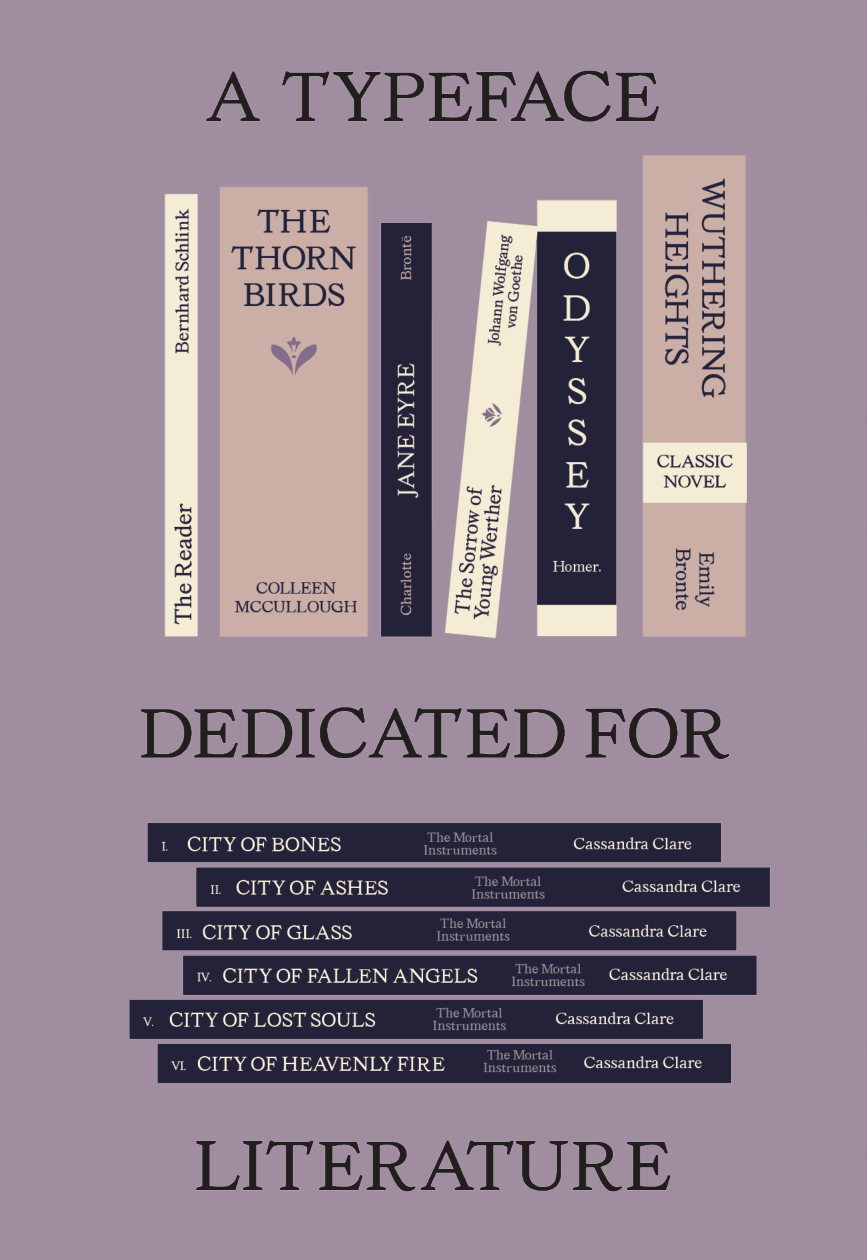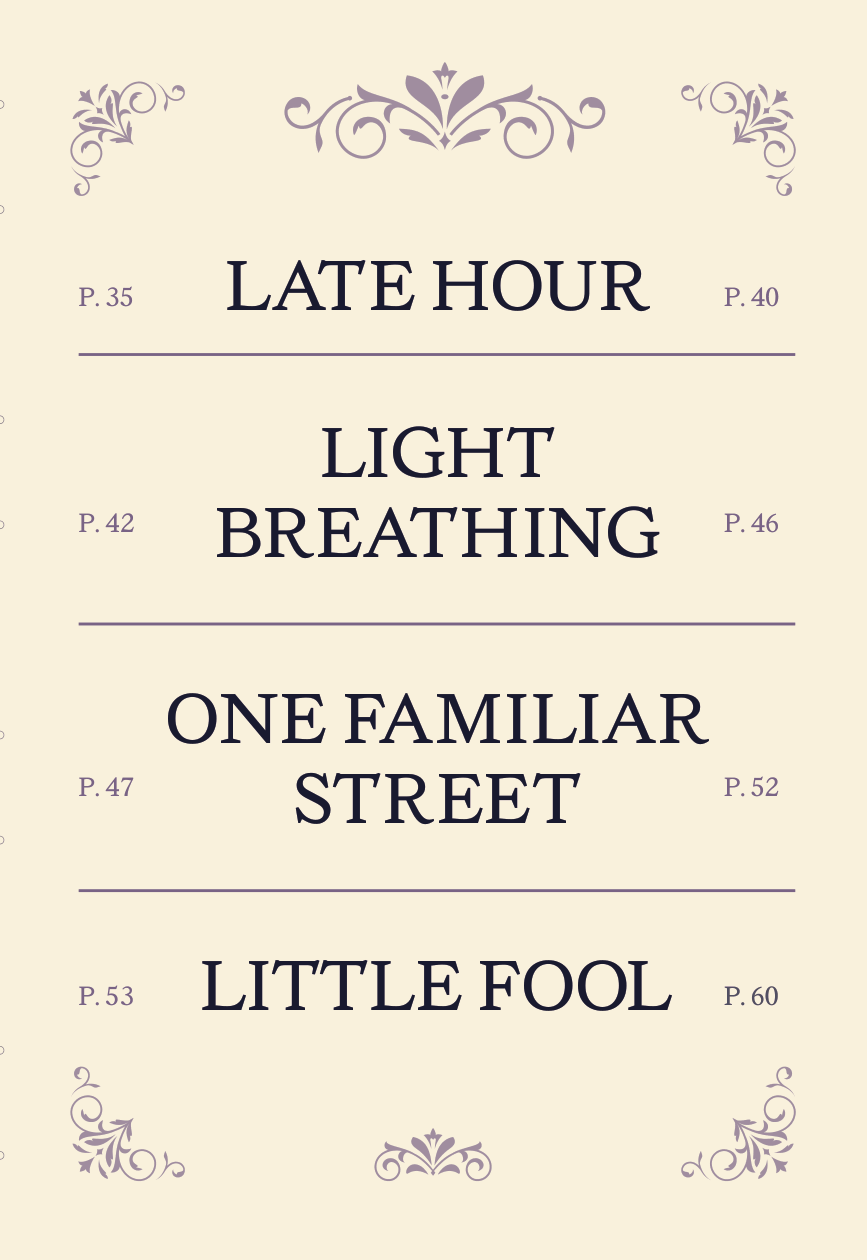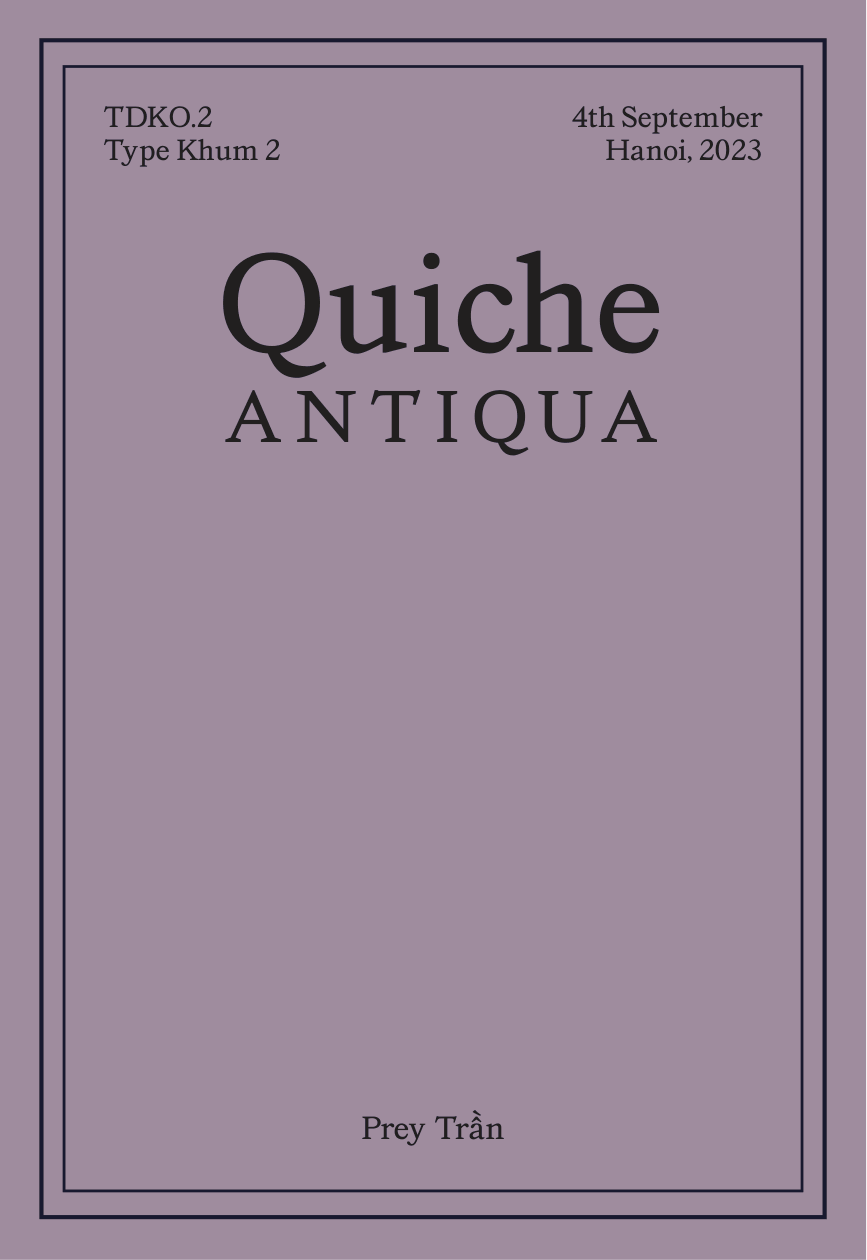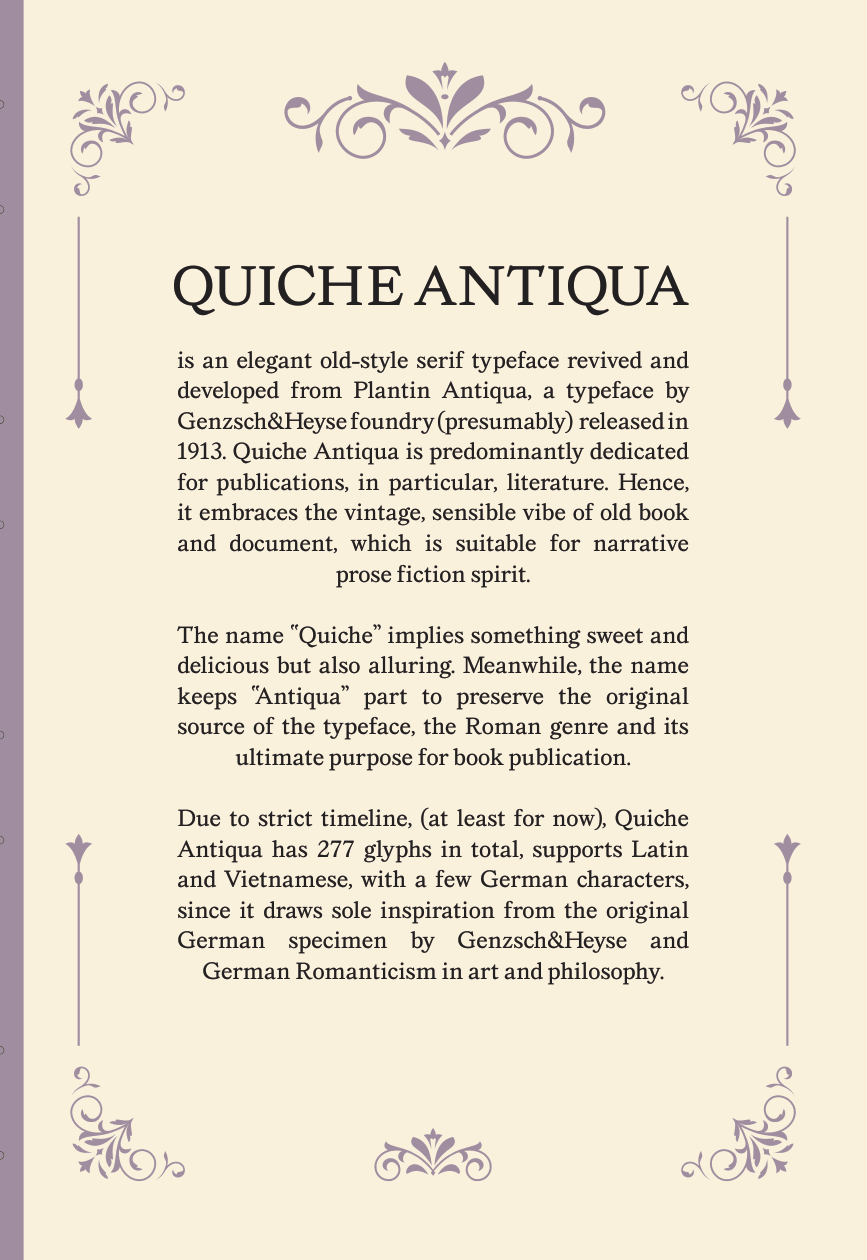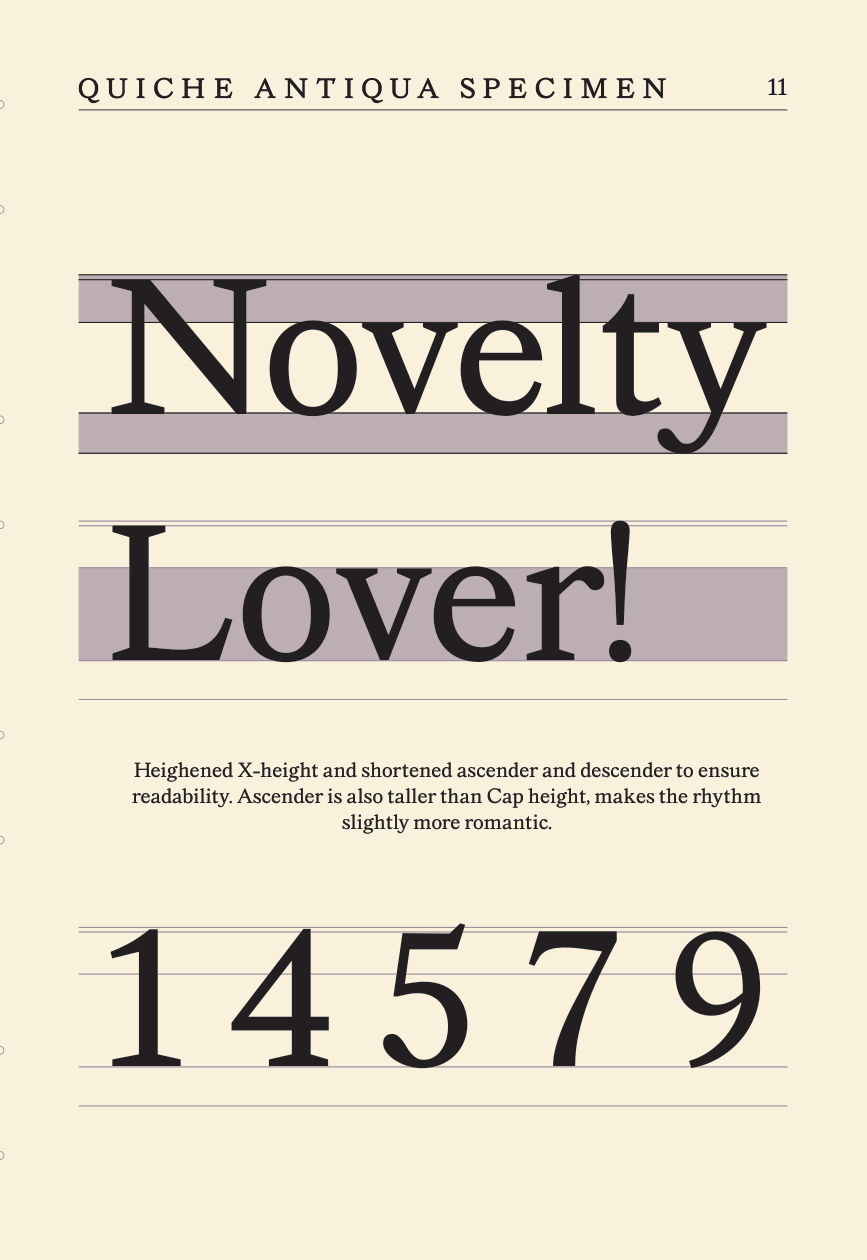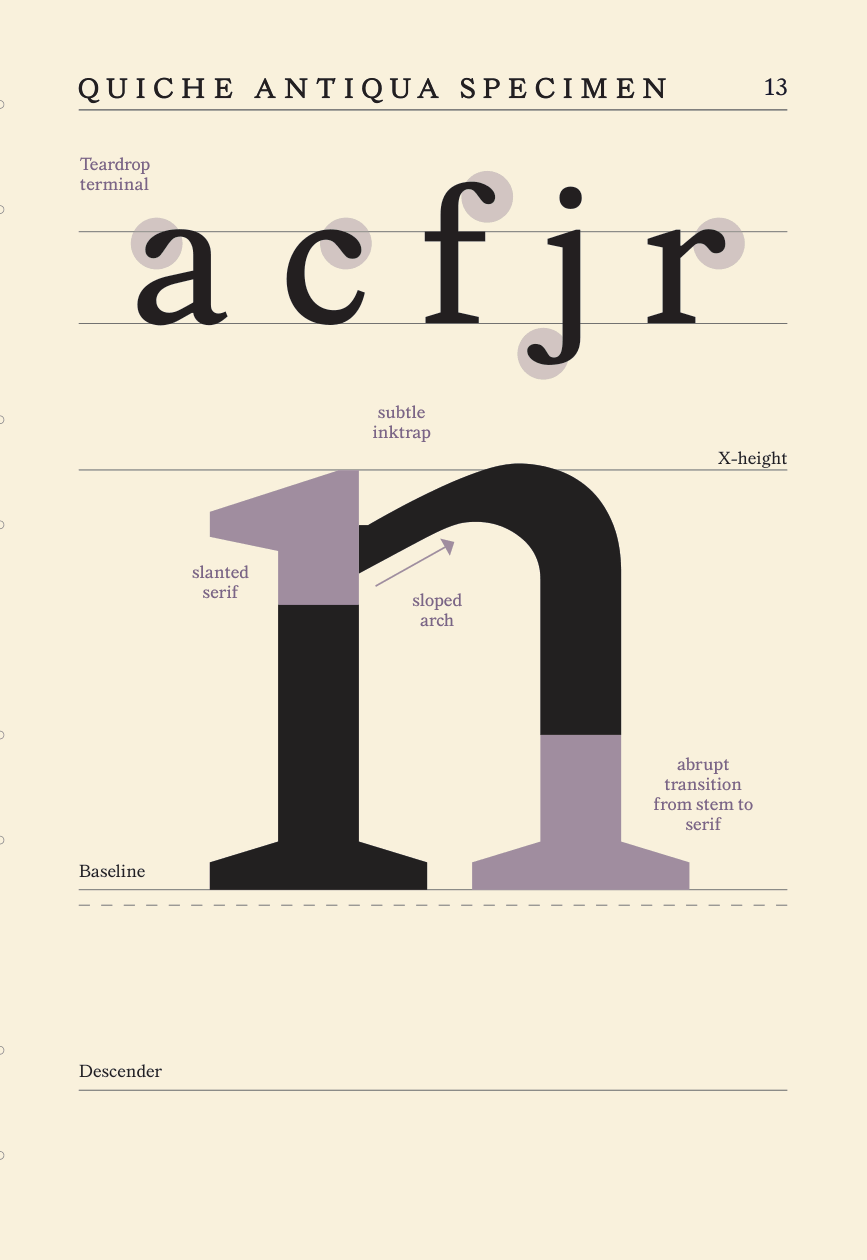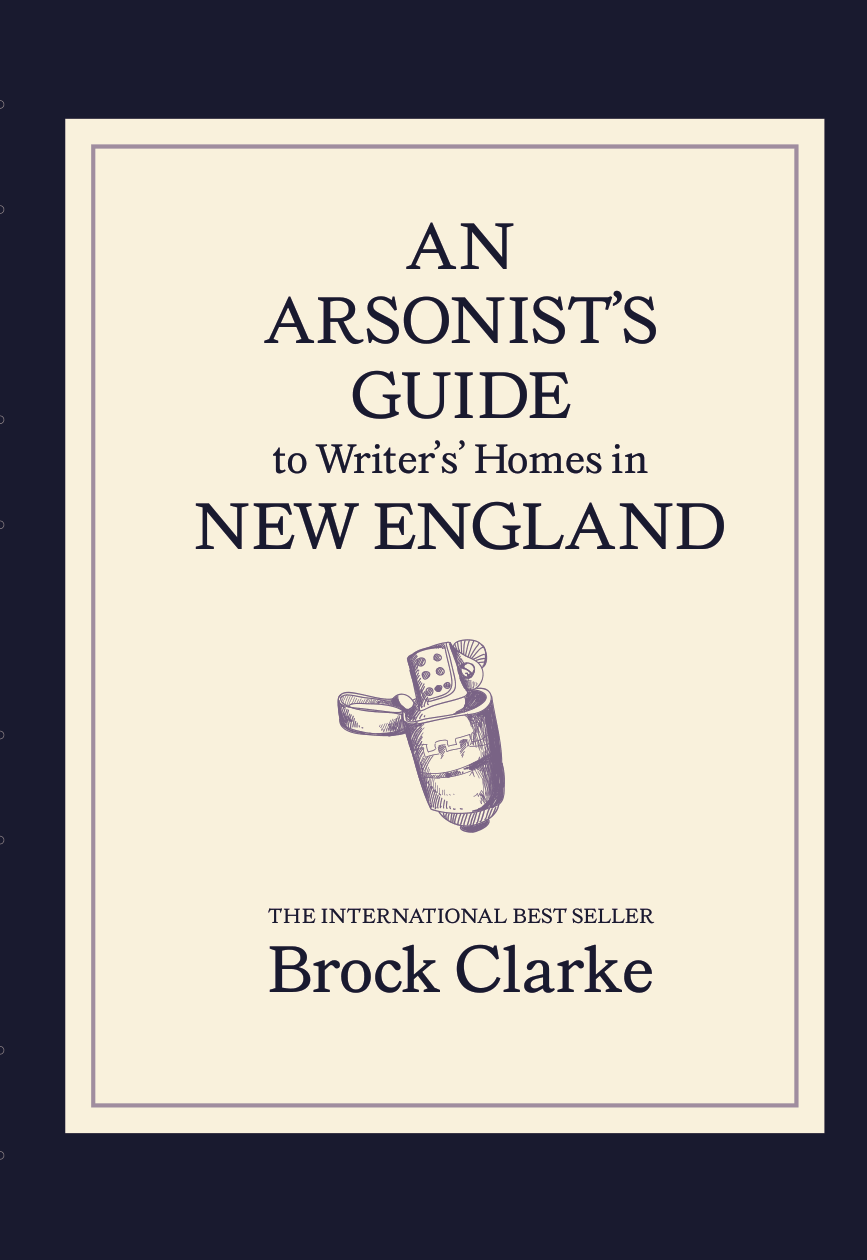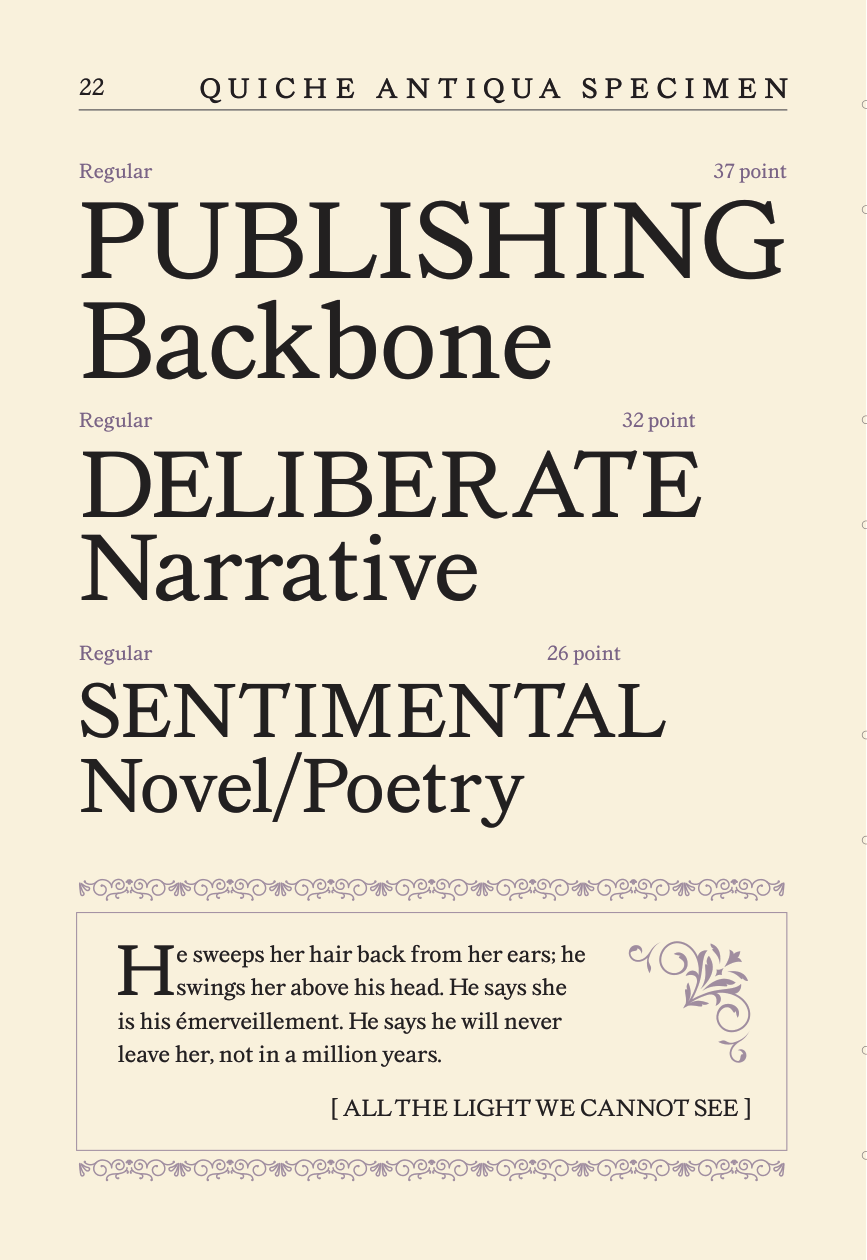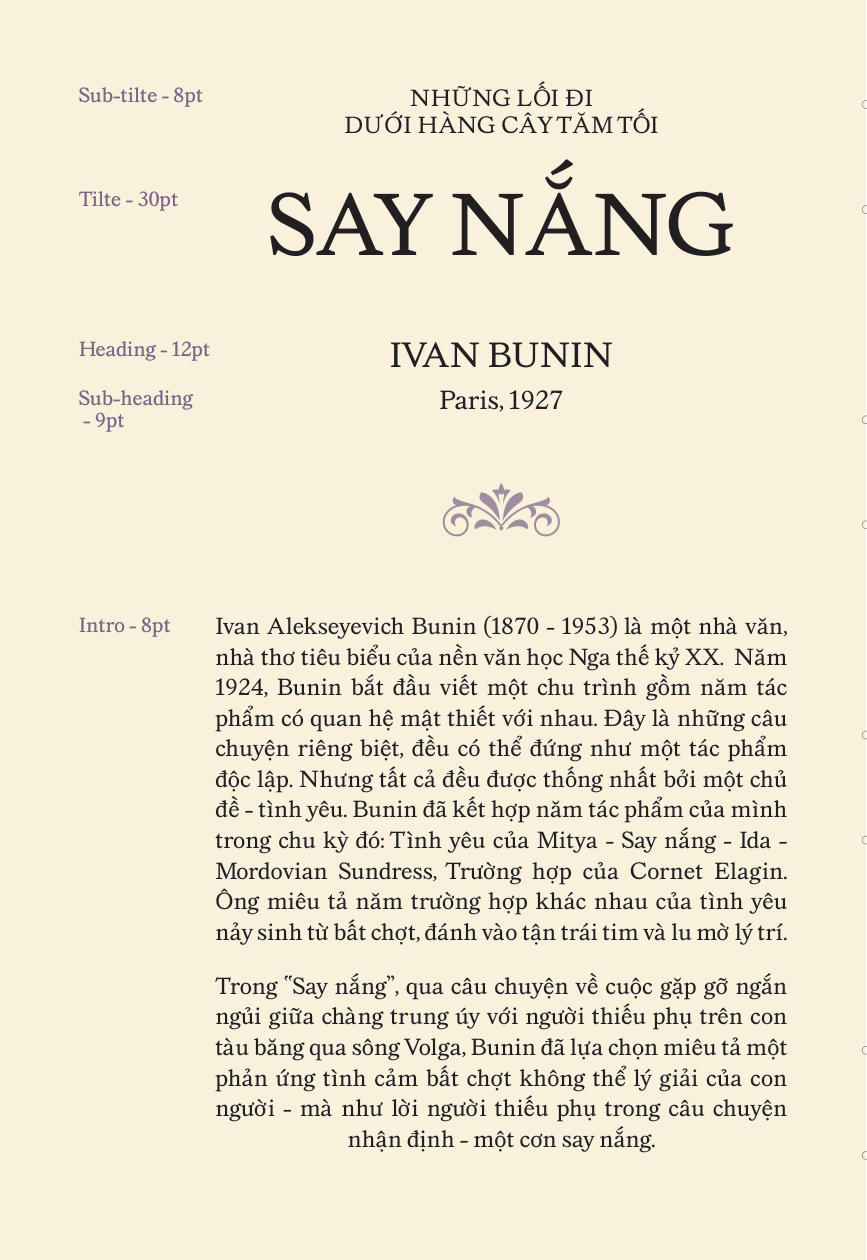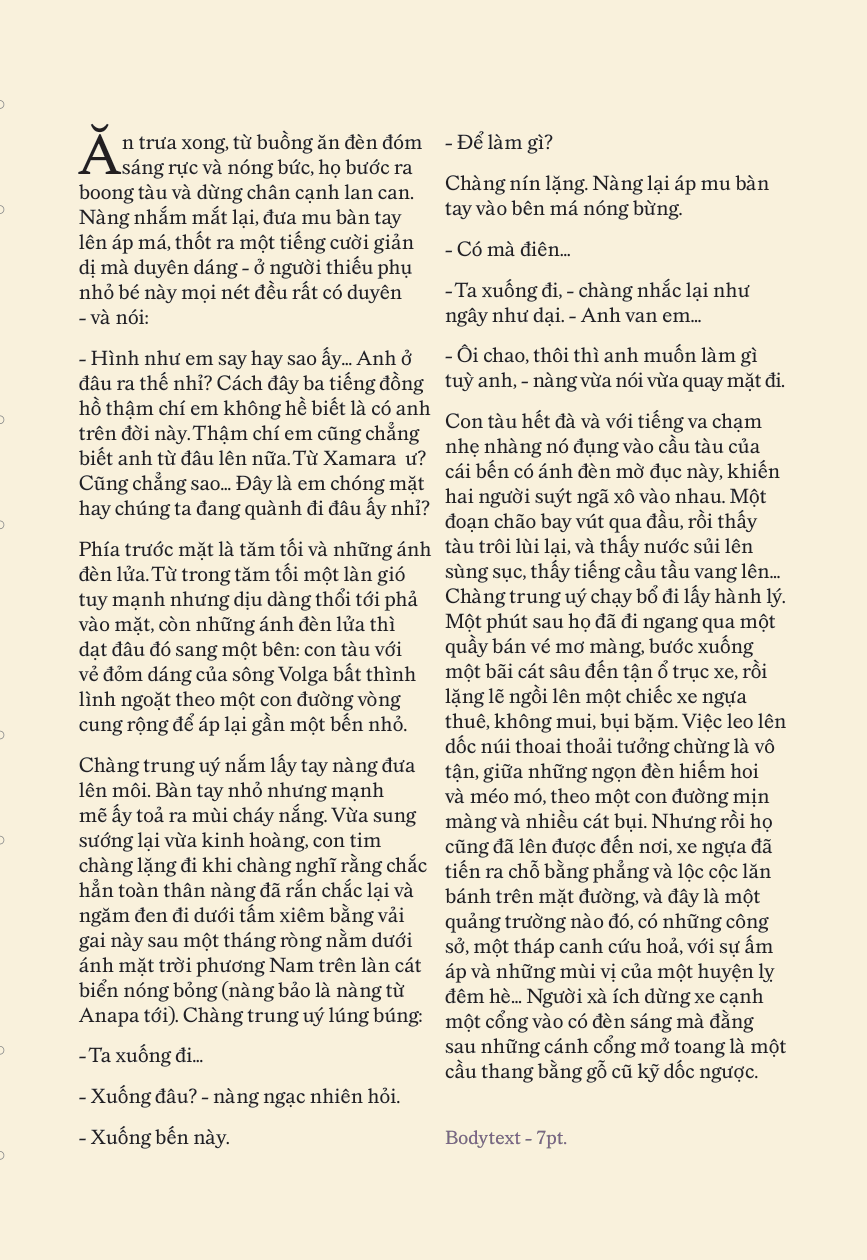
Quiche
Về Quiche: Quich Antiqua là một kiểu chữ serif old-style thanh lịch, được phục dựng và phát triển từ Plantin Antiqua, một kiểu chữ của xưởng đúc chữ Genzsch & Heyse (được cho là) phát hành vào năm 1913. Quiche Antiqua chủ yếu được thiết kế dành cho xuất bản, đặc biệt là văn học. Tên gọi “Quiche” gợi đến sự ngọt ngào, hấp dẫn nhưng cũng đầy lôi cuốn. Trong khi đó, phần “Antiqua” được giữ lại nhằm bảo tồn nguồn gốc của kiểu chữ, thuộc nhóm chữ La Mã, cũng như mục đích cốt lõi của nó là phục vụ xuất bản sách.
Old Style Serif
Text
Prey Trần
Quiche
Novelty
Quiche
Publishing
Quiche
Sentiment Prose
Quiche
Deliberate Narrative
Quiche
Genzsch & Heyse is a Hamburg-based type foundry founded by Emil Julius Genzsch (1856–1906). It was later taken over by Linotype in 1963.
Quiche
Plantin Antiqua appears to have had its first—and only—recorded appearance in a specimen book, likely published around 1929, based on the date shown on the specimen cover. However, the Luc Devroye online archive lists the typeface’s release date as 1913. From the original source, only a limited set of characters can be retrieved: Latin letters and numerals in Regular and Kursiv (Italic). No further information about the typeface or its designer is available. As a result, beyond its revival, Plantin Antiqua presents strong potential for expansion into a more extensive and comprehensive character set. It remains unclear whether Plantin Antiqua was influenced by Monotype Plantin. Nonetheless, the name “Plantin Antiqua” still suggests an association with Plantin’s legacy—particularly its emphasis on print quality and its use in publication contexts.